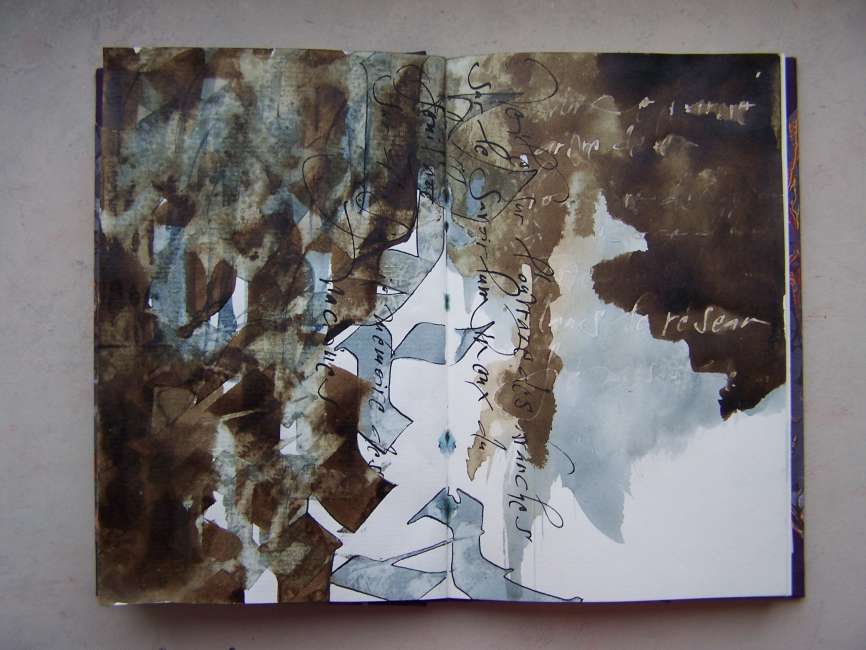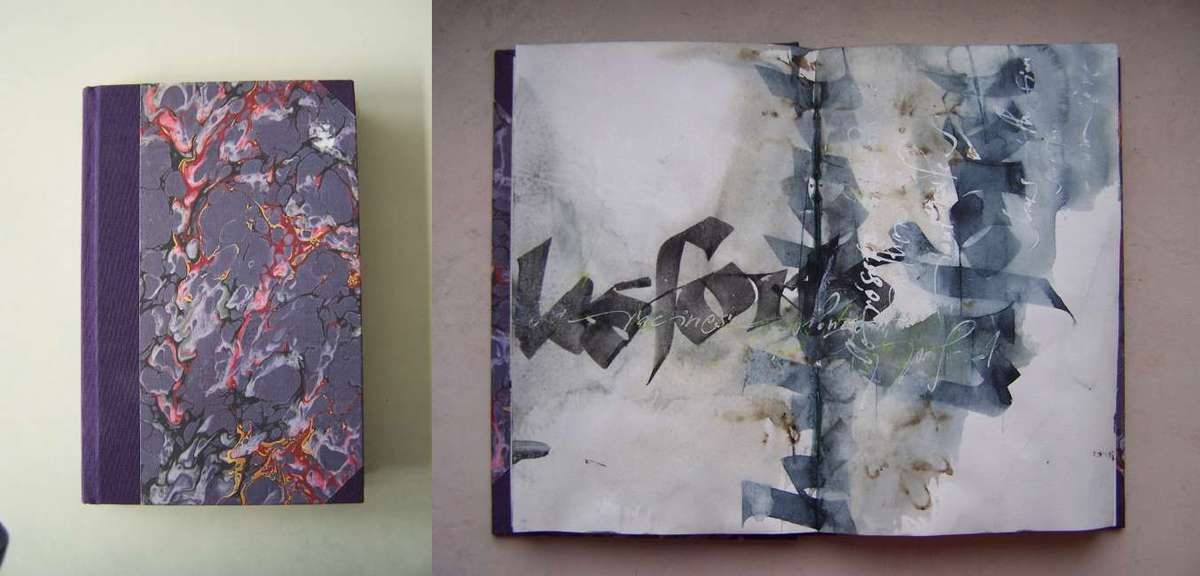
Au fond de l'aber, une gravure de Jean-Yves André
En cette période de fêtes, je me suis fait un petit plaisir : une petite eau-forte de Jean-Yves André. Lorsque J-Y André l'avait publiée sur son blog, elle m'avait tout de suite fait envie, le sujet et son traitement me parlaient.
Il m'a donné le choix entre plusieurs tirages et j'ai choisi une épreuve d'artiste, c'est-à-dire un des deux premiers tirages d'essai. L'aspect final du tirage dépend entre autres paramètres du papier. Celui utilisé pour les épreuves d'artiste, un papier aquarelle, donne un rendu très fin du trait, délicat. C'est la raison de mon choix.
Il m'a aussi montré le croquis de départ, un simple dessin au crayon bille sur un papier quelconque de format A4, le tirage du premier état de la plaque - avant l'ajout de traits supplémentaires, et quelques tirages sur papier Balkis dans des nuances d'encre différentes.
La technique employée est la gravure sur cuivre à l'eau forte : la plaque est recouverte d'un vernis, l'artiste grave son dessin à la pointe sèche sur le vernis puis la plaque est plongée un certain temps dans de l'acide pour creuser les traits dans le métal. Le vernis est alors enlevé et la plaque est prête pour l'encrage et le passage dans la presse.
Dimensions de la gravure : 4 x 6 cm.
L'ivre de peintures : I'm searching I.
Fin septembre dernier, j'ai commencé un carnet de recherche axé sur la composition de fonds de matières et de couleurs. Soixante-quinze doubles pages plus tard, je viens de le refermer.
J'ai travaillé soit sur des doubles-pages de 14 x 28 cm, soit sur deux formats carrés de 14 x 14 cm qui se répondent. Les pages sont enduites puis travaillées aux pigments, aquarelles, encres et peintures acryliques.
Bonsaï & Calligraphie, Michel Fornasero
Samedi dernier, j'ai reçu en service presse un ouvrage de Michel Fornasero "Bonsaï & Calligraphie" publié par les éditions ARQA. Je viens d'en finir la lecture, et j'en ressors enrichie, avec l'envie de le relire plus lentement pour prendre le temps de creuser plus profondément les pistes de réflexion qu'il ouvre, sur la calligraphie et sur le rapport de l'homme à la nature et à l'esthétique.
"Totalement habité par le continent asiatique, Michel Fornasero ne se départira plus de ses passions pour les arbres, qui prennent racines dans son enfance et aujourd'hui même dans l'art si complexe du Bonsaï qu'il pratique en amateur éclairé ; pour les arts martiaux aussi, Judo et Kendo, qu'il exerce avec rigueur. La pratique assidue de la calligraphie latine, art de la belle écriture en Occident, et son amour pour les arts extrême-orientaux, calligraphie chinoise et japonaise, ainsi que pour le sumi-e (art ancien de la peinture asiatique) qu'il découvre avec des enseignants, jusqu'en Chine, lors de l'un de ses voyages, l'amènent à réfléchir avec conscience, depuis de nombreuses années, sur les liens historiques et artistiques qu'enseignent respectivement ces deux mondes. " Extrait de la notice consacrée à l'auteur.
Michel Fornasero met en parallèle tout au long de son ouvrage art du Bonsaï et art de la calligraphie. Deux progressions parallèles se déroulent calmement tout au long de l'ouvrage, dans des phrases claires voire parfois lumineuses, nourries de pratique et d'un corpus de connaissances historiques distillées à juste escient. En refermant le livre, je me suis dit que ce texte était à l'image d'un bonsaï qui présente lignes de forces et espaces de respiration : il offre un surplus de conscience du beau.
Dans le texte :
" La calligraphie n'est pas la belle écriture.
La calligraphie est l'utilisation des signes écrits comme moyen d'expression artistique. L'expressivité et la signification vont différencier une belle écriture d'une calligraphie. Le calligraphe latin s'appuie sur la connaissance du corpus des alphabets qui évolua tout au long de l'histoire. Au-delà, il effectue un travail artistique à partir de signes harmonieux respectant l'équilibre des règles des arts plastiques."
"...le calligraphe est le seul maître de son destin, pourrions-nous dire. Il pose la limite de l'interprétation du signe, de la simple lisibilité d'un texte à l'expression abstraite..."
"L'encre est la marque visible de l'énergie déposée par l'outil."
"Le papier reste finalement comme une sorte de peau sur laquelle le calligraphe matérialise sa vie. La vie est dans le geste, elle coule par l'outil, se visualise par le médium et c'est bien, comme son nom l'indique, le support qui enregistre cette déposition. Si l'outil est l'instrument de l'action, le médium est celui de la pensée, quant au support, il est le récepteur de la mémoire."
Conclusion : un bel ouvrage de réflexion pour nourrir une pratique calligraphique ou simplement des interrogations sur l'esthétique.
L'essai d'origine, réalisé pendant le passage de l'extrait musical: